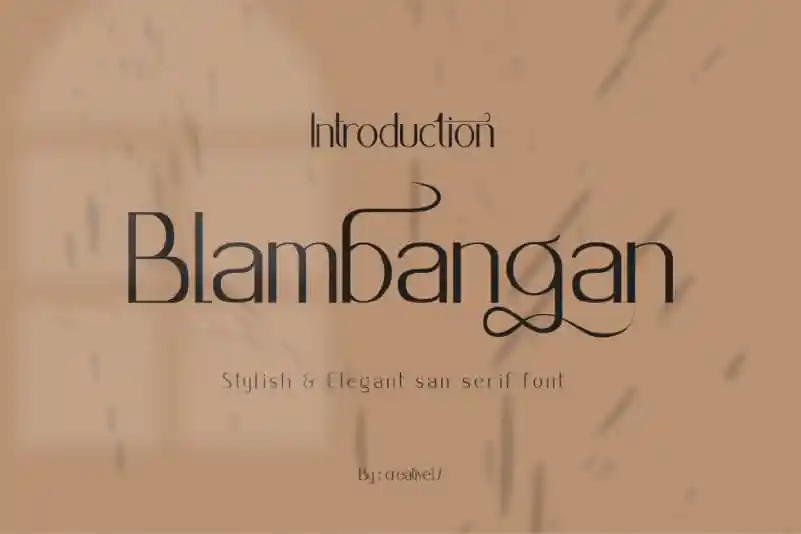
Blambangan Sans Serif Font – Download Grátis
A Blambangan Sans Serif é uma fonte sem serif que combina elegância moderna com nuances cuidadosamente pensadas. Perfeita para projetos grandes e pequenos, desde identidades de marca até cartões de casamento, logotipos e diversos outros trabalhos gráficos. Esta font inclui um conjunto completo: letras maiúsculas e minúsculas, números, pontuação, suporte multilinguístico e mais ainda ligatures e alternativas de letras. Ela é perfeita para quem busca uma fonte sofisticada e versátil, capaz de capturar a essência do design moderno em qualquer projeto.